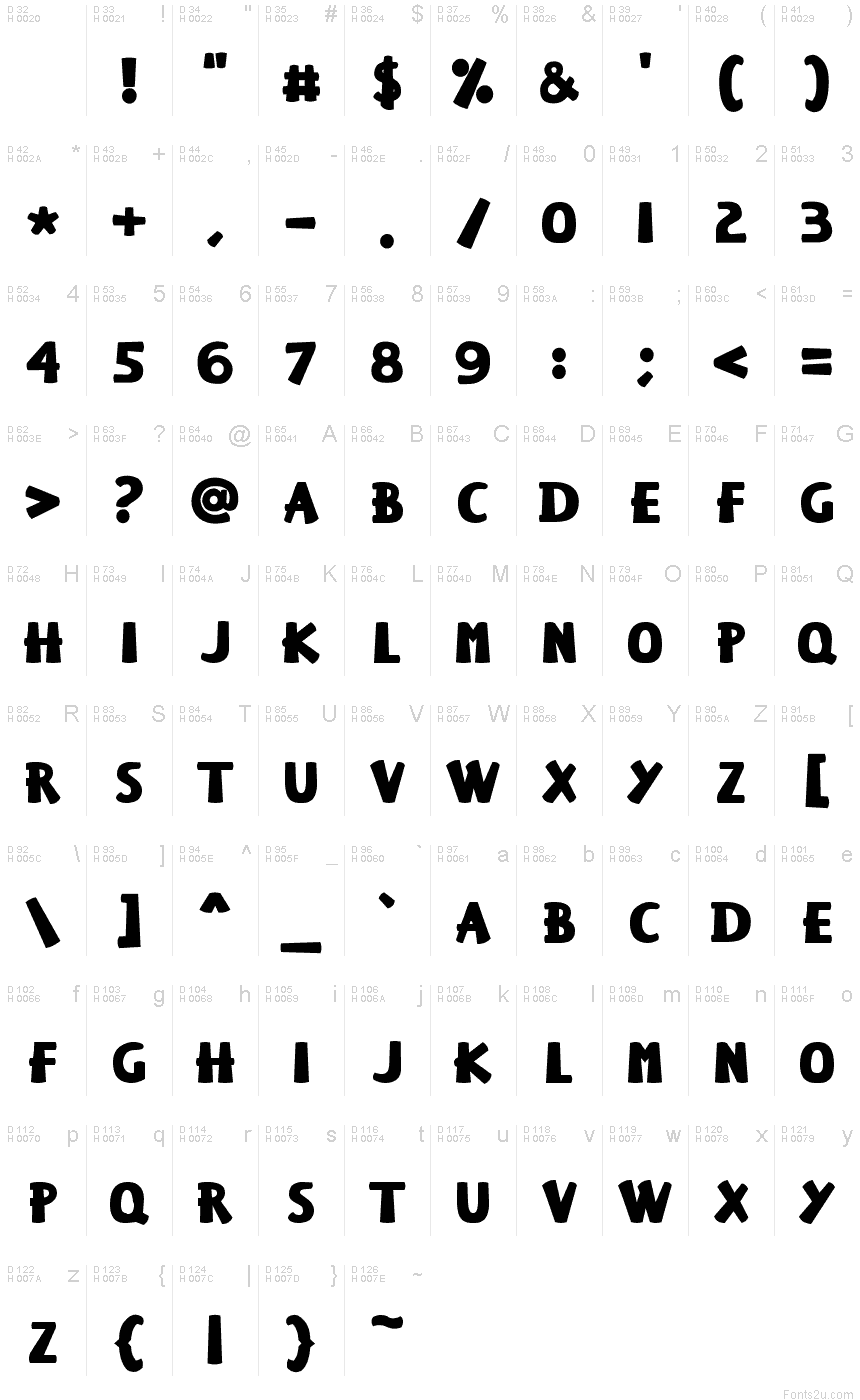
Písmo Keiser Sousa od Czcionki.com je bezplatný komiksový font s výrazným, inkoustovým vzhledem. Každé písmeno působí dojmem, že bylo ručně vyříznuto a je mírně asymetrické, jako by bylo na své místo doslova vtěsnáno, což dodává nadpisům hravý a živý rytmus. Robustní tahy a těsné rozestupy vytvářejí syté černé bloky, které okamžitě upoutají pozornost, zatímco jemná nepravidelnost udržuje celkový dojem uvolněný a zábavný, nikoli tuhý či korporátní.
Tento bezplatný font skvěle vynikne na obálkách komiksů, titulcích dětských knih, plakátech na párty, herních logách, náhledech pro YouTube, či na hravých nálepkách a merchandise. Keiser Sousa nejlépe funguje ve větších velikostech, kde jeho tlusté křivky a nepravidelné obrysy naplno předvedou svou kreslenou energii. Pro menší text nebo doplňující informace ho kombinujte s čistým, neutrálním bezpatkovým písmem, aby Keiser Sousa zůstal v centru pozornosti jako hlavní prvek.